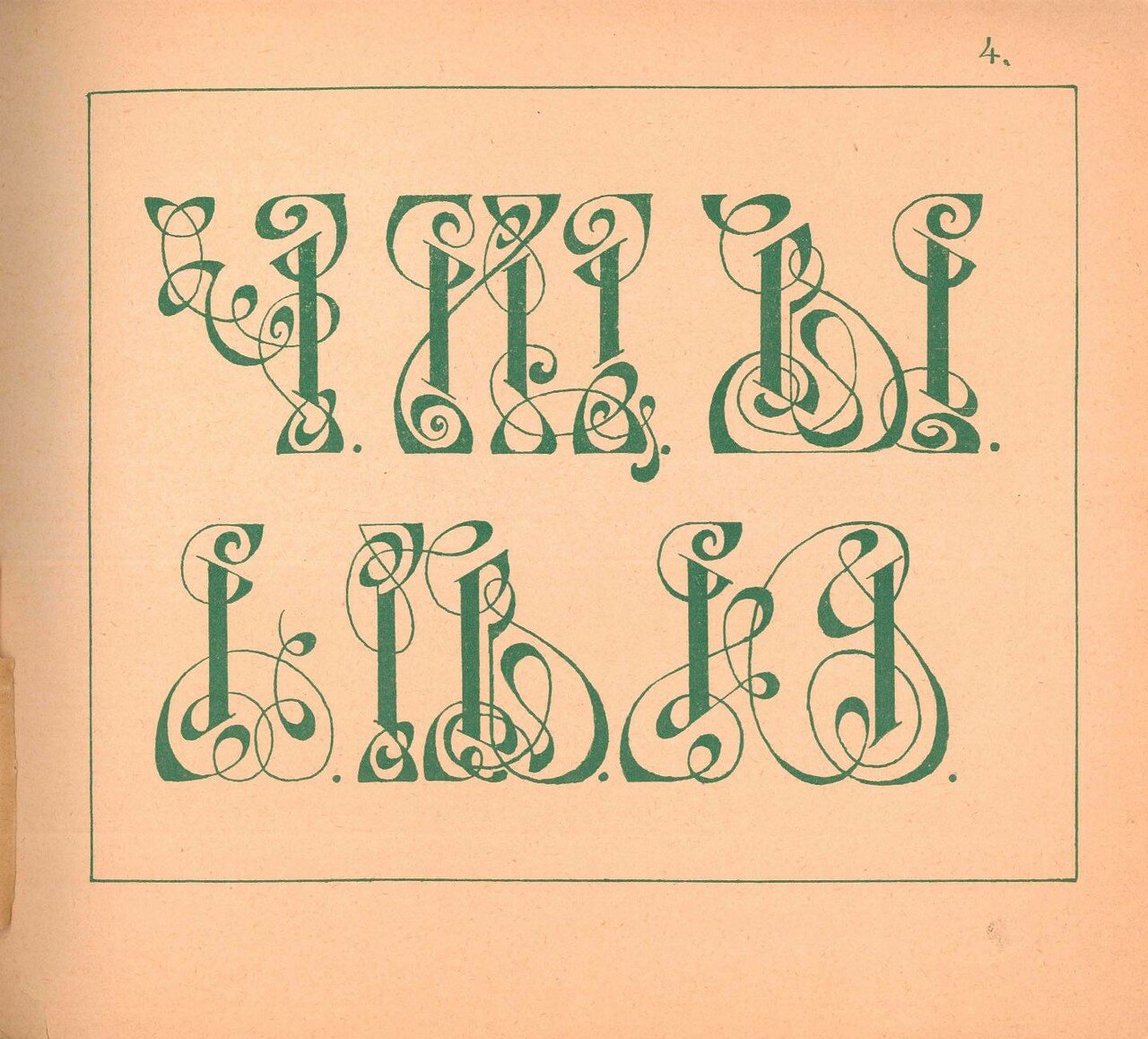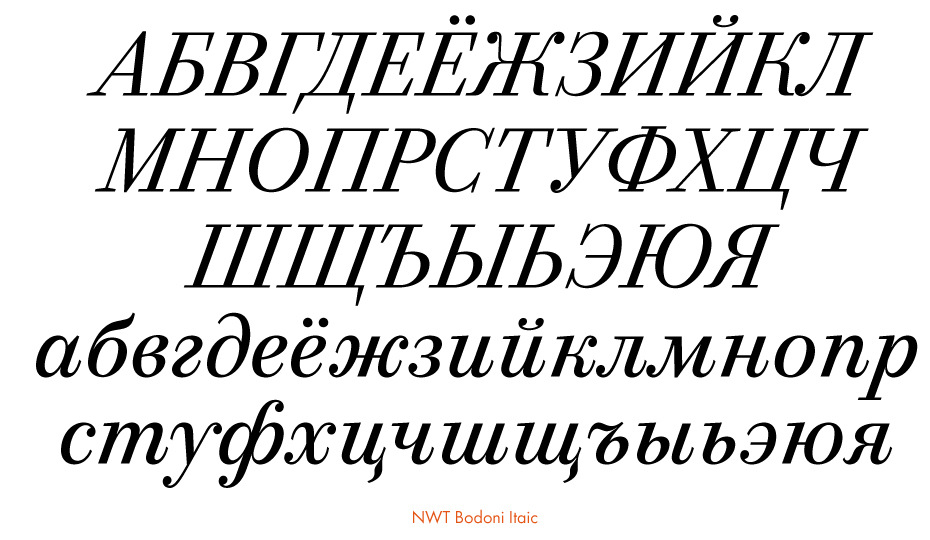
Каким шрифтом печатают книги? — блог книжной типографии Printleto
Выбор шрифта для книги — проблема, которая волнует начинающих создателей художественной и научной литературы.Задача дизайнера книжной типографии состоит в том, чтобы подобрать идеальный шрифт для вашей книги. Главное правило того, что вы прогадали со стилем шрифта, — это удобство чтения. Когда вы читаете книгу, вы погружаетесь в историю, наполняетесь эмоциями автора, познаете новую информацию, и последнее, что вы должны замечать — как выглядит шрифт.
Какой размер шрифта используется в книгах?
Шрифт — неотъемлемая часть в создании композиции книги. Книжные дизайнеры разделяют два понятия: гарнитура и шрифт.Шрифт — это определенный образец, например, Helvetica Narrow Italic. А гарнитурой обозначают набор шрифтов одного рисунка, но разных размеров (кеглей) и начертаний.
Шрифт также делят на 2 группы: наборный и рисованный. Наборный шрифт используется для самого текста издания. Рисованный шрифт применяется для визуального оформления, дизайна книги, в частности, на обложке, переплете и титульном листе. Рисованный шрифт создает уникальный стиль книжного произведения.
При выборе шрифта учитывайте 3 особенности: гарнитуру, начертание и кегль.
Наборный текст рекомендуется печатать обычным, курсивным, полужирным или курсивным полужирным шрифтом в выбранной гарнитуре. Добиться запоминающегося дизайна можно используя всего пару шрифтов.
Что ещё влияет на выбор шрифта? Конечно, бумага. Если у вас мелованная бумага, то не используйте тяжелые, контрастные шрифты, они выглядит броско. А на газетной бумаге с трудом читается тонкий и изящный шрифт.
Для каждого кегля есть свое персональное название: кегль 6 пунктов — бриллиант; кегль 4 пункта — диамант; кегль 6 пунктов — нонпарель; кегль 7 пунктов — миньон; кегль 8 пунктов — петит; кегль 9 пунктов — боргес; кегль 10 пунктов — корпус; кегль 12 пунктов — цицеро; кегль 14 пунктов — миттель.
Для каждого типа книжного издания определен наиболее читаемый размер кегля. Так, для художественной литературы подходит 10-12-ый кегль. Для остальной печатной продукции оптимальным считается 9-14-ый кегль.
Не забывайте и о том, что размер наборной строки тоже играет свою роль в удобочитаемости. Рекомендуем использовать не более 50-55 знаков в одной строке.
На выпуск книжных изданий существует ГОСТ, по которому определяется кегль и стиль шрифта. В большинстве печатных изданий используют Times New Roman, Garamond, Bodoni, Academy, Georgia.
Роль шрифта в оформлении книги
Шрифт — способ передачи текста в книге. Это его главная и существенная роль.
Шрифт с засечками и без. Для основного текста издания рекомендуем использовать шрифт с засечками или без засечек, потому что такие шрифты являются «классическими» и не вызывают дискомфорта при длительном чтении. Декоративные шрифты подходят для заголовков, оглавления или других элементов книги, на которых нужно заострить внимание.
Печатные шрифты. Courier и другие шрифты, которые используются в печатных машинках, — это моноширинные шрифты. Отличить их можно по одинаковой ширине всех знаков. Избегайте таких шрифтов для создания основного текста книги. В качестве исключения, моноширинные шрифты используют для заголовков глав, и в других случаях, где вам требуется характерный шрифт.
Как выбрать шрифт для детской книги?
Если вы пишите детскую книгу и не знаете, какой размер шрифта лучше подойдет, то прочтите рекомендации по выбору шрифта для каждой возрастной группы. Для детей дошкольного возраста (до 7 лет) подойдет шрифт в 16 или 20 пунктов, так как дети только начинают читать и знакомиться с буквами, их должно быть хорошо видно.Для детей первой младшей группы (7-9 лет) 14 и 16 пунктов для первоклассников, 12 и 14 пунктов для второго класса. Для детей второй младшей группы (10-11 лет) 11 и 12 пунктов для третьего класса, 10 и 11 пунктов для четвертого класса.
Дети среднего и старшего возраста (12-17 лет или 5-11 классы) могут читать шрифт любого размера.
какой лучше подобрать шрифт для татуировки?
Не всегда татуировки в виде рисунка способны выразить всю полноту эмоций и мыслей, которые хочется показать. Вот почему так популярны среди молодежи тату, представляющие собой надписи.
Выбирая надпись, ее слова, язык, способ начертания, стоит особенно внимательно подбирать шрифты для тату: смысл надписи и стиль написания букв не должны представлять собою диссонанс.
Помимо смысла фразы, большое значение имеет красота и стиль написания. Особенно важное значение приобретает шрифт для тату надписи, когда она сделана на иностранном языке. В любом случае, стиль букв может придать особый оттенок смыслу написанного, а также выразить эмоции и характер обладателя татуировки. Даже пара слов, удачно расположенных на какой-либо части тела, может стать настоящим шедевром и украшением, подчеркивающим индивидуальность человека.
Широко распространенные готичные шрифты для тату характеризуются резкостью и прямотой линий, четкими углами, часто заостренными концами букв. Такие жесткие и прямые линии как нельзя лучше подходят для мужчин, отражая их решительный и твердый характер. Древняя цитата, выполненная средневековым шрифтом Gothic (а именно с тех времен берет свое начало этот тип начертания букв) будет выглядеть эффектно и значительно.